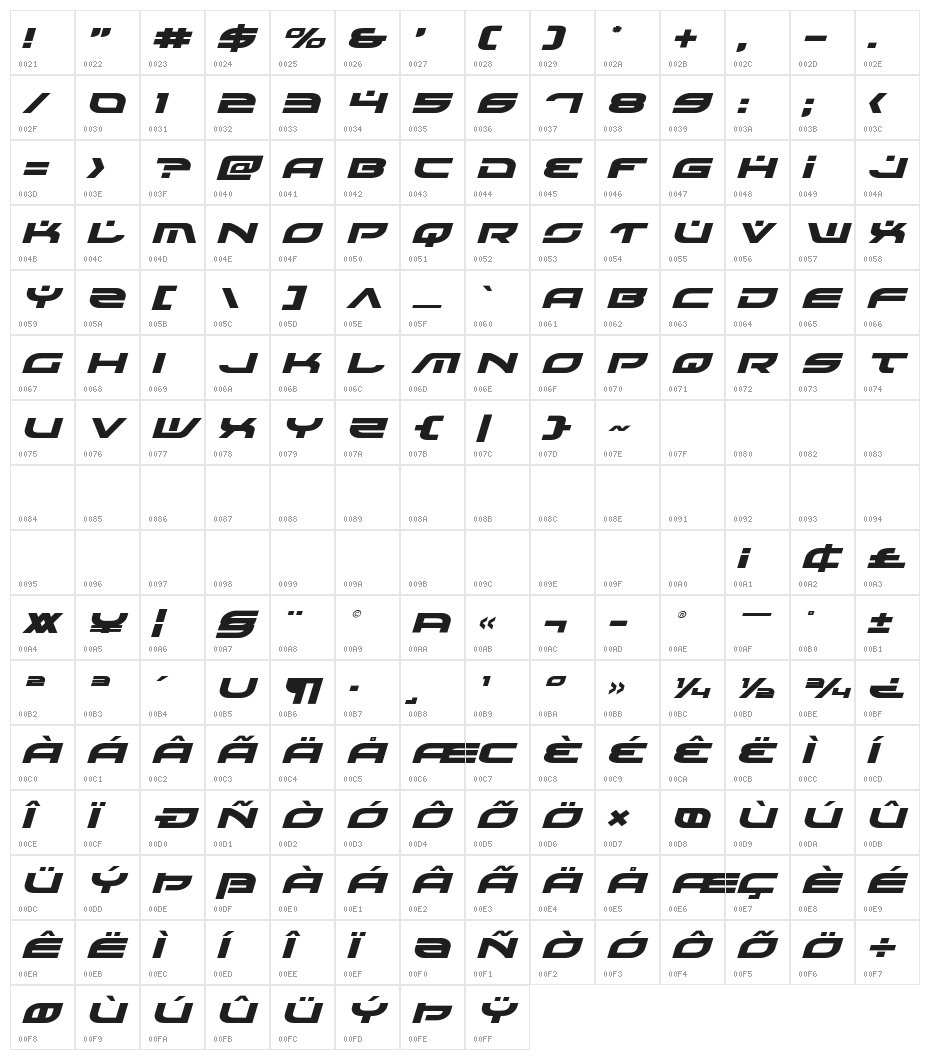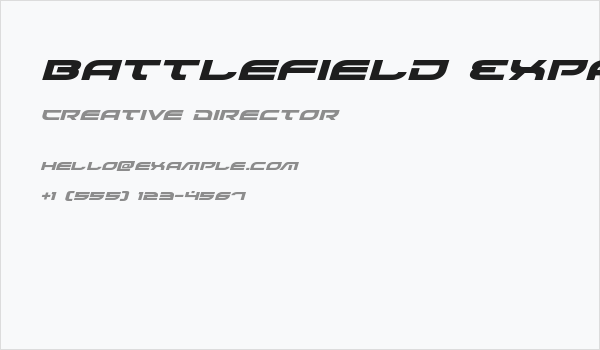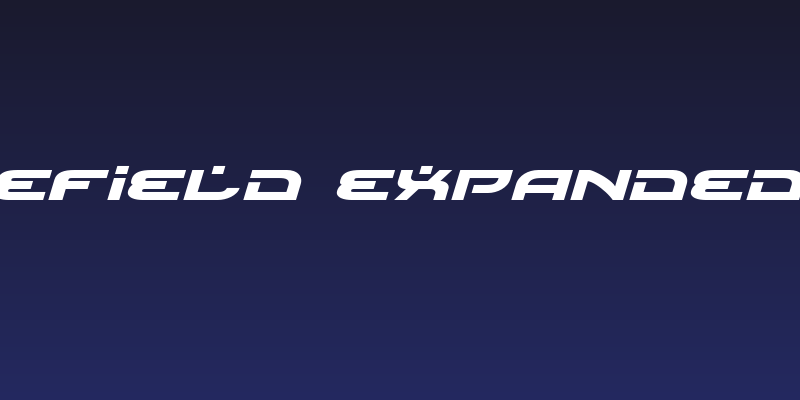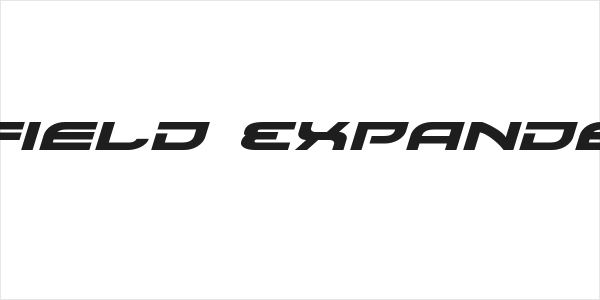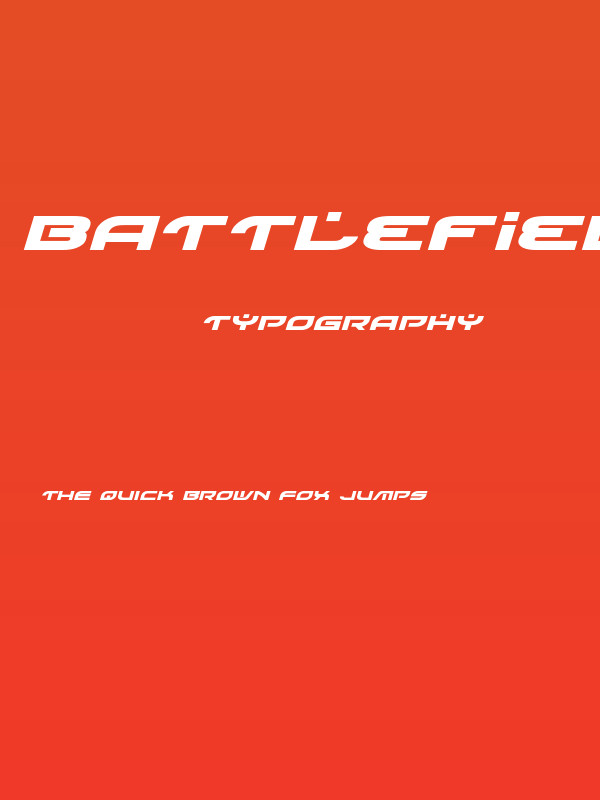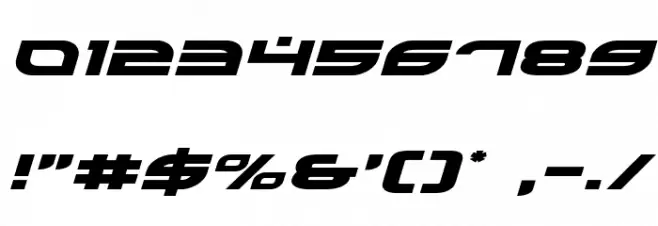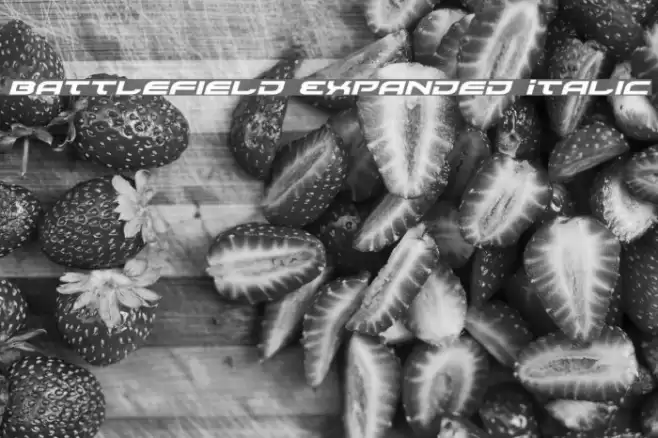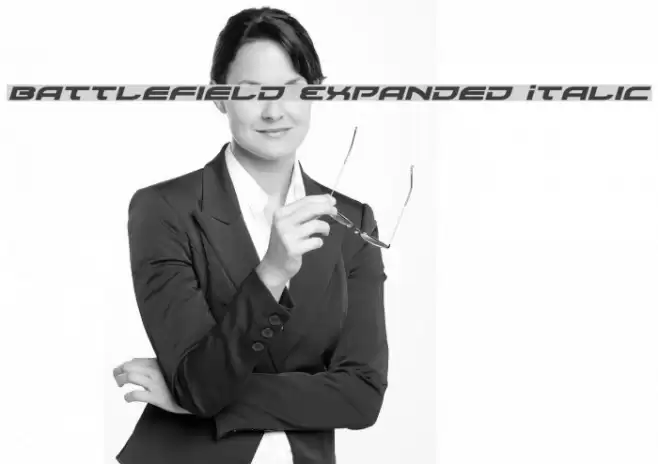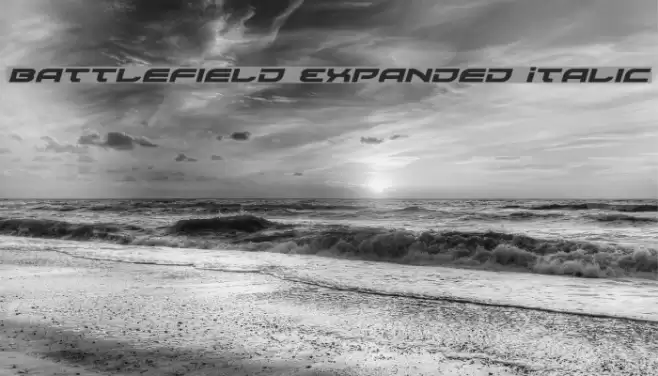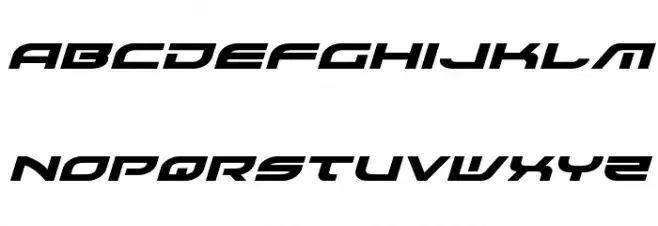
Battlefield Expanded Italic Font
| おすすめプロジェクト | Ideal for video game titles, sci-fi movie posters, technology branding, and sports event promotions. |